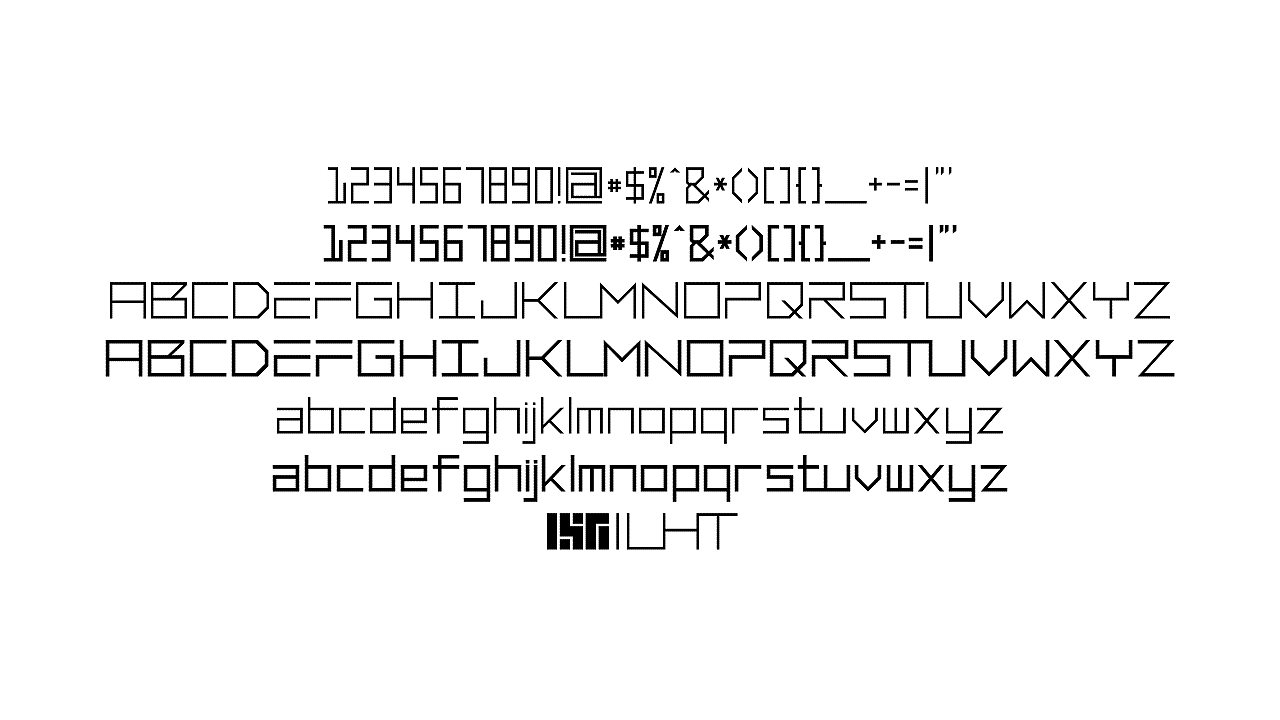
LHTFONT
LHTFONT字体介绍
LHTFONT的作者是宜春的LHT02,作者自称该字体为本人困在家里闲得慌做出来的一款英文字体,其实这个字体很早以前就准备去做了,打算是用来配合自己的作品用的。"₤"被替换成了作者自己的LOGO,用艺术字体的一般也不会去闲的专门去输入这个符号。大写字母"L"与"T"以及小写字母"t"会连字,这是故意的。整个字体里面除了几个半辈子不会去打出来的符号以外不含有任何曲线。字体斜线的宽度可能会粗细不一,已经尽力了。。。LHTFONT字体首发于站酷,作者声明免费商用。唯一的要求就是,如果作品有引用素材列表的话,署名LHT02(或者LHT,能署名尽量,非硬性要求)
LHTFONT字体应用示例